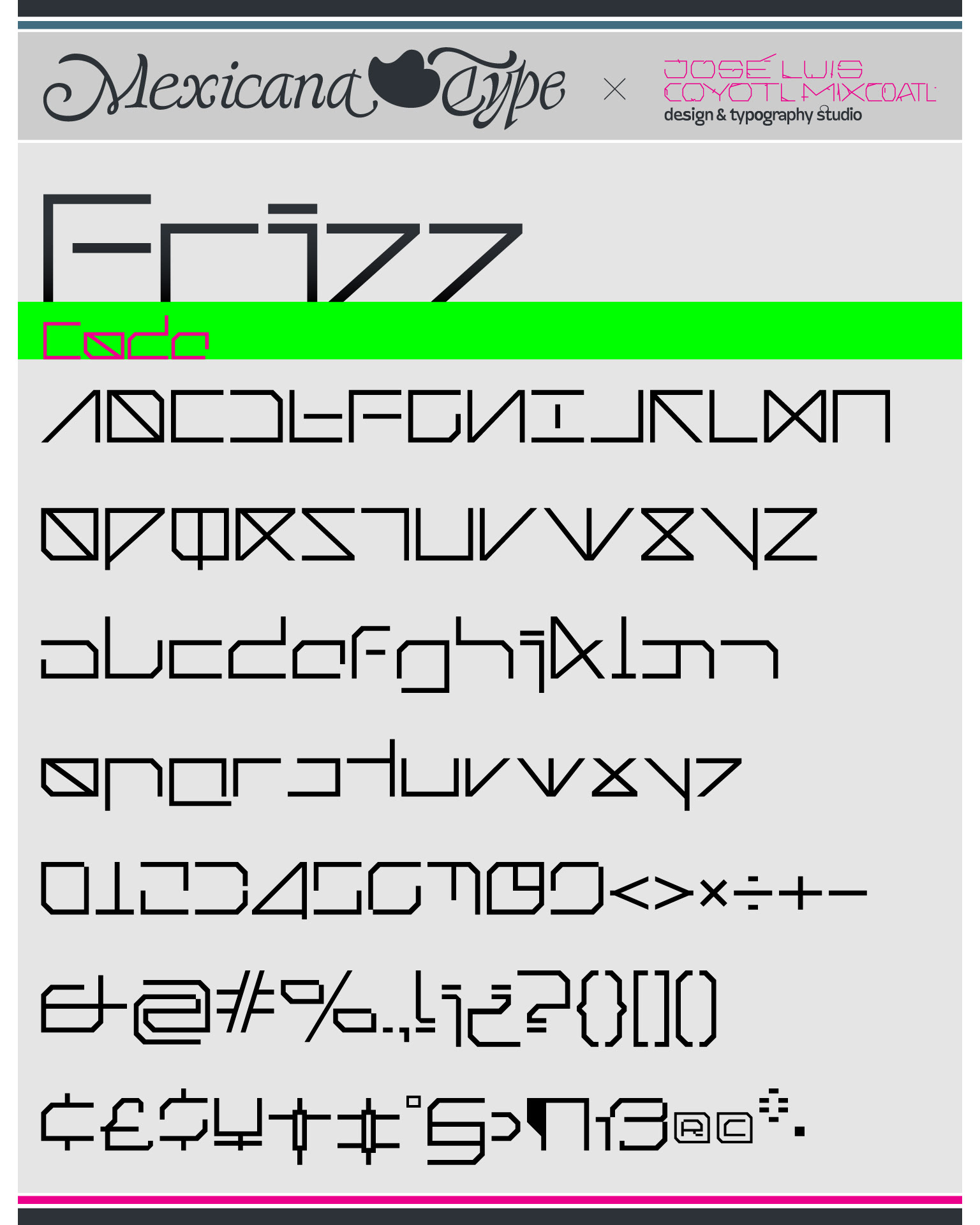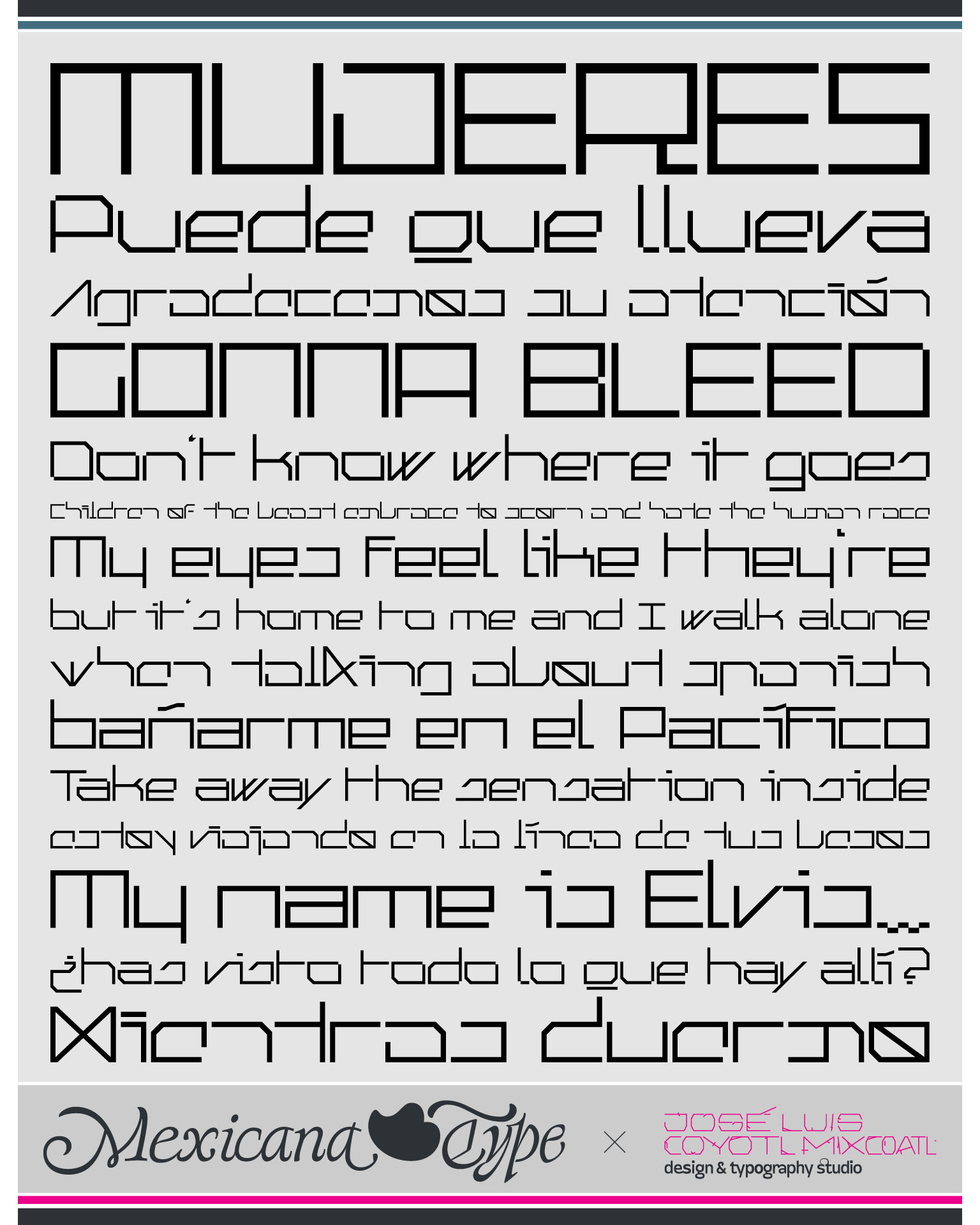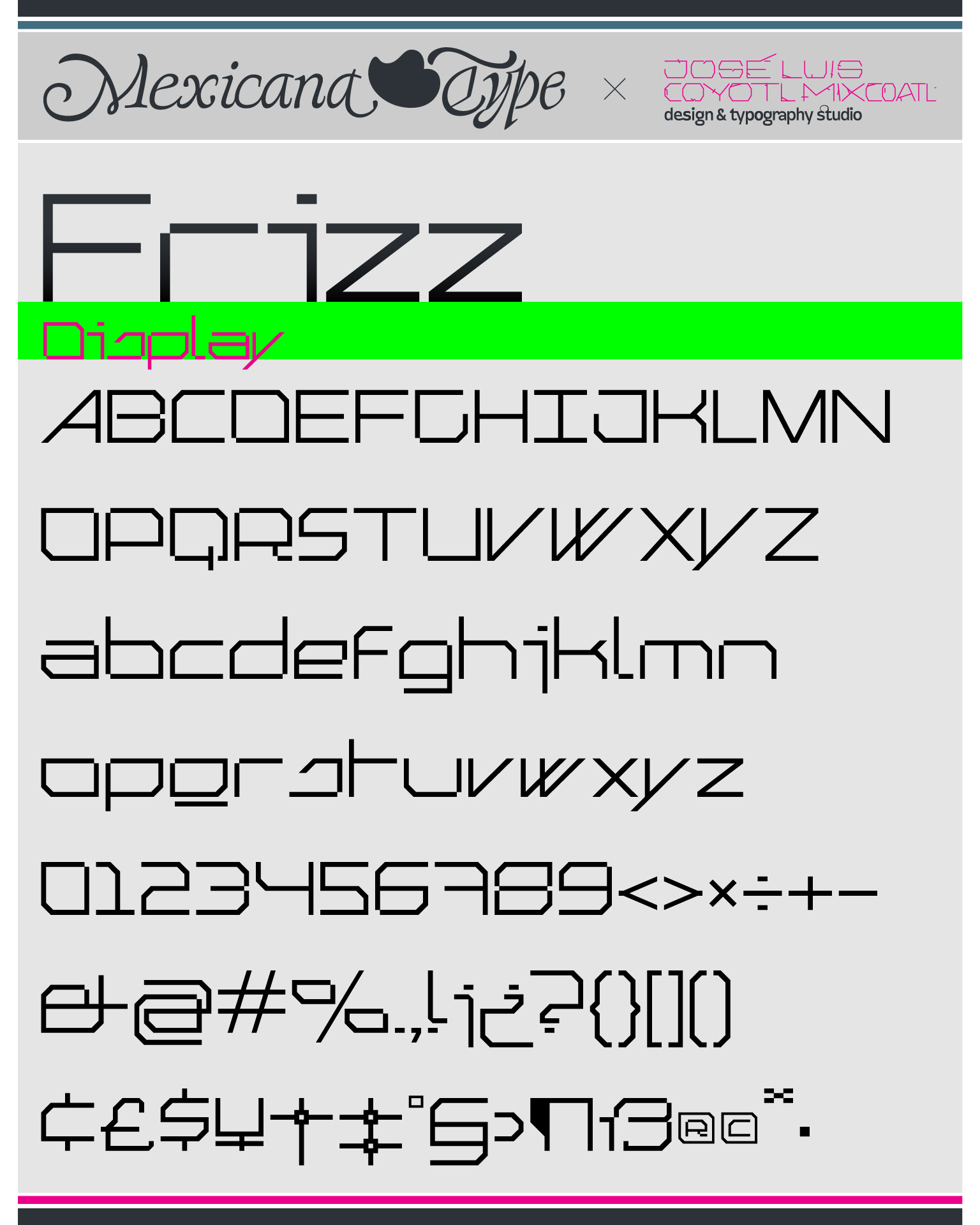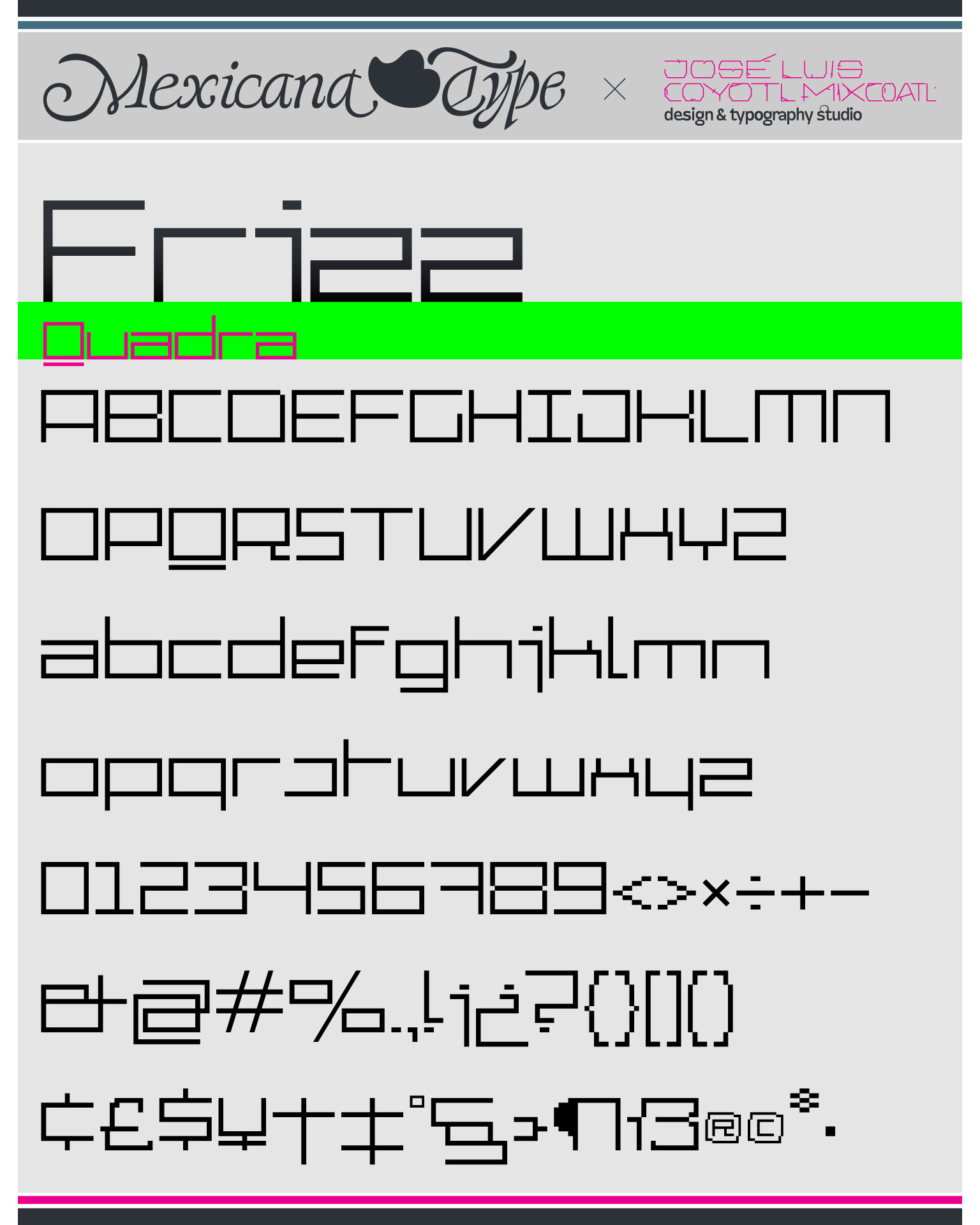
MxT Frizz se desarrolló para la interfase de mi sitio web alrededor de 2004. Siendo una de las áreas que mas he desarrollado, decidí diseñar elementos tipográficos e íconos, complementándose con MxT Cubomatics.
MxT Frizz es un juego de líneas rectas y diagonales geométricas, simétricas y modulares, estructuradas de manera que pudiese articularse para componer texto que pudiera conectarse en distintas formas. Pensada para funcionar en títulos aunque originalmente está diseñada bajo principios de tipografía para pantalla, también funciona en otros medios tradicionales de maneras que se vuelve muy versátil.
Sus tres versiones: Quadra, Display y Code, son en sí un juego desde lo modular a lo experimental que incluso pueden ser combinadas entre si como alternates debido a la compatibilidad en sus proporciones, con un juego de legibilidades que no necesariamente buscan la funcionalidad de la lectura rápida, pero justo en ello recae su gracia. Sus proporciones extendidas y el flujo de su texto en bloque le dan una uniformidad en la formación de cuerpos de texto, aunque no necesariamente sirve para textos largos, sino para palabras o frases cortas con un sentido estético y muy singular.